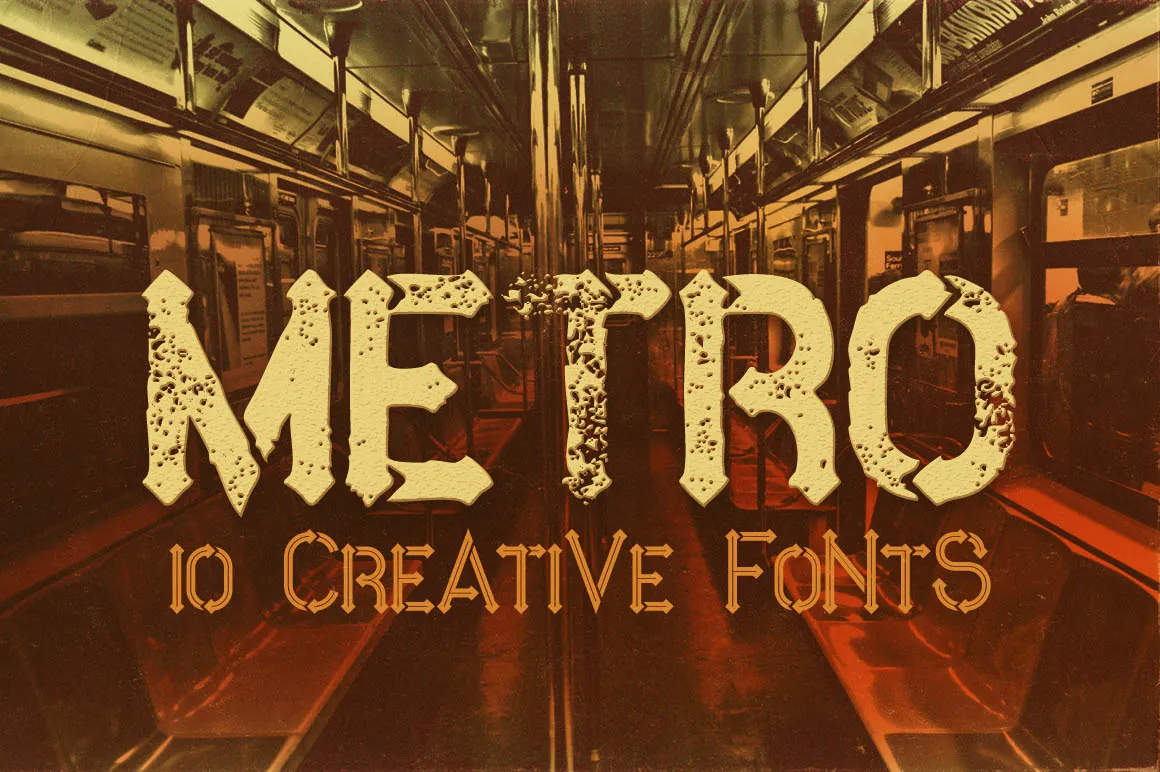
Metro Grunge Font – Download Grátis
Esta fonte ‘Metro Grunge Font’ é uma ótima escolha para projetos criativos modernos que buscam um estilo retro e grunge. Desenvolvida pela MIIM Design, ela oferece os elementos necessários para criar designs atraentes que capturam o espírito dos anos 80 e 90 de maneira inovadora e atual. Com seu design agradável e forte, a Metro Grunge Font é ideal tanto para títulos quanto para as seções do texto, tornando-a uma opção perfeita para os designers em busca de algo diferenciado e vibrante. Ideal tanto para trabalhos digitais quanto impressos, essa fonte atende à tendência dos grunge modernos, oferecendo um toque único que pode dar seu projeto aquele toque definitivo de criatividade.